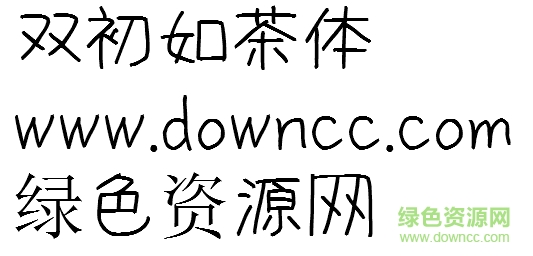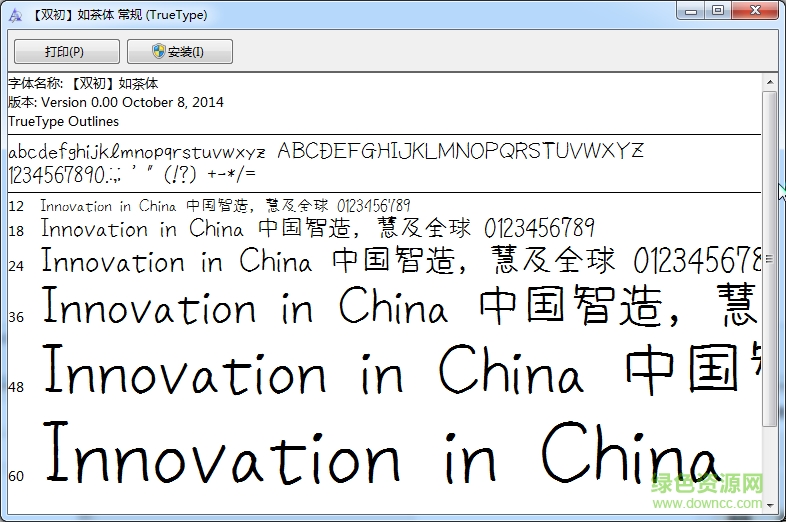
雙初如茶體是一款獨(dú)特造型的pop字體,字跡有著不規(guī)整的設(shè)計(jì),單整體十分和諧,無論是數(shù)字、字母還是漢字都有著各自的特色,讓人心生好感,喜歡的朋友請來綠色資源網(wǎng)免費(fèi)下載吧!
如茶體,字如其名,清淡如茶回味無窮,字里行間跳動著飄逸淡泊的韻味,讓人品嘗如茶般的恬靜和美好,可用于海報(bào)設(shè)計(jì)、平面設(shè)計(jì)等領(lǐng)域!
雙初如茶體字體是一款用于漫畫設(shè)計(jì)方面的字體,字體充滿童真的手寫風(fēng)格,有著非常美觀和諧的字體結(jié)構(gòu),而且字體的筆畫流暢有力,辨識度很高,可作為廣告字體和宣傳標(biāo)語字體使用!